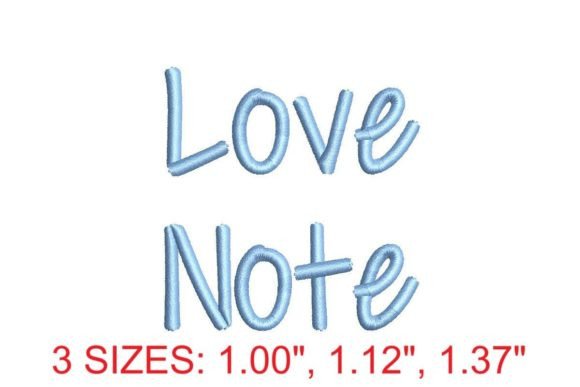
Love Note Embroidery Font
Mencari elemen reka bentuk yang sesuai boleh menjadi mencabar, tetapi Love Note Embroidery Font menawarkan koleksi luar biasa yang menaik taraf karya anda serta-merta.
Sama ada anda mencipta produk POD (Print on Demand), jemputan perkahwinan atau grafik media sosial, Love Note Embroidery Font amat bersesuaian.
Petua pakar: Gabungkan elemen ini dengan fon pelengkap untuk mencipta reka bentuk yang unik dan menarik perhatian.